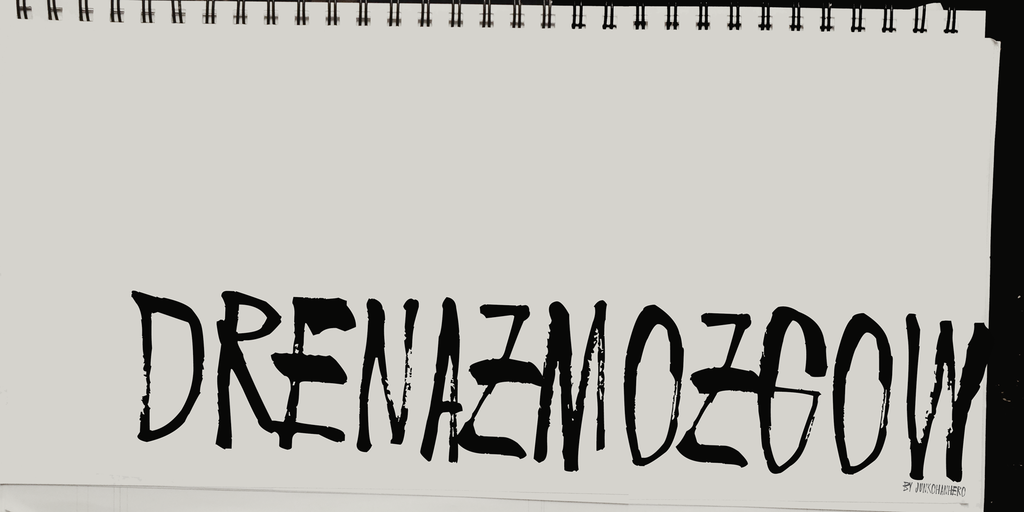
A Drenazmozgow Font é uma fonte de escrita chinesa livre para uso pessoal. Para quem está planejando projetos comerciais com essa incrível fonte, podemos oferecer a opção de um licenciamento comercial. Você pode adquirir esse benefício pagando 15 euros ou $20 através do PayPal. Após o pagamento, basta nos enviar um e-mail para confirmar que recebemos sua quantia. Esta fonte única é perfeita para criações gráficas de alta qualidade. Estamos ansiosos para ver seu projeto nela!